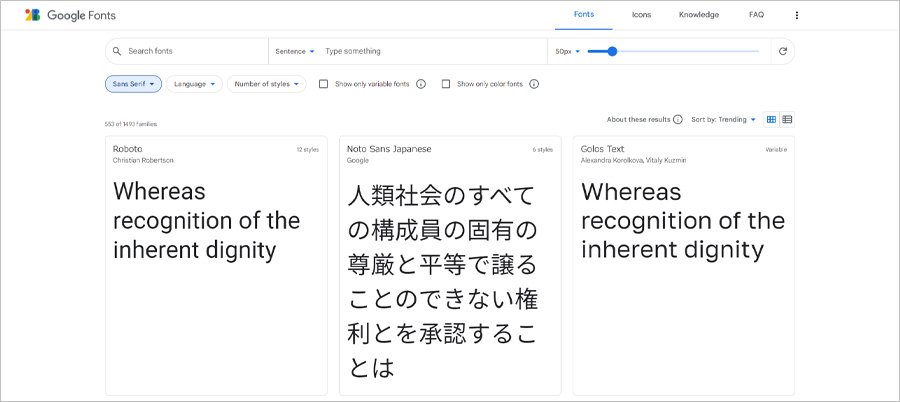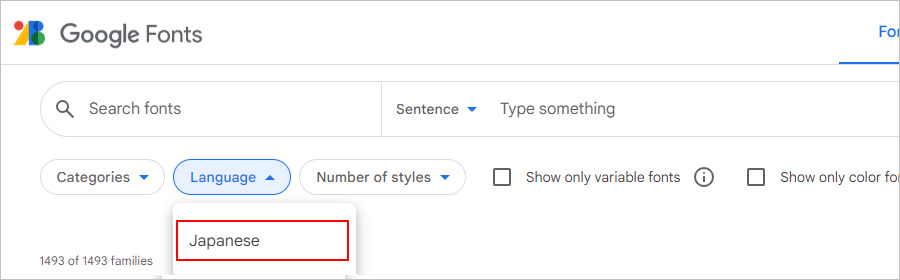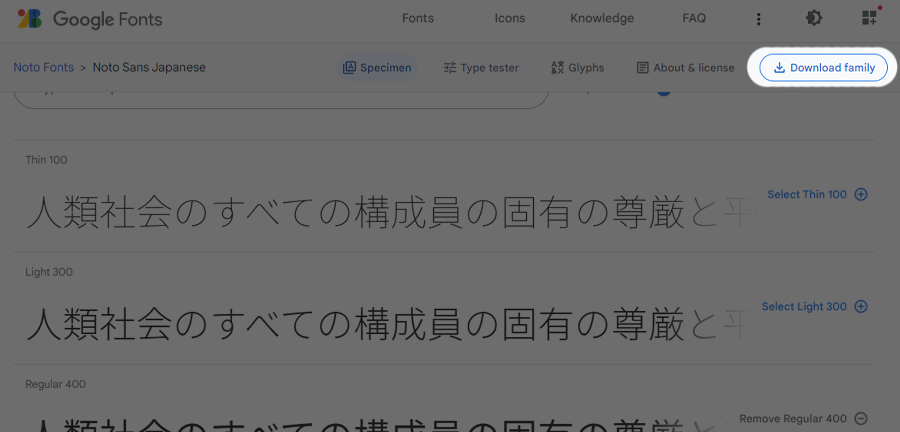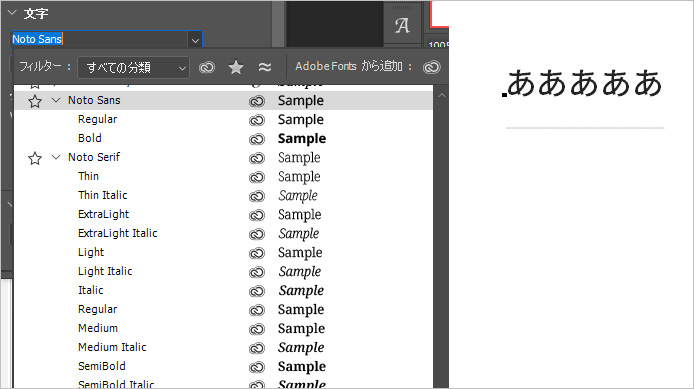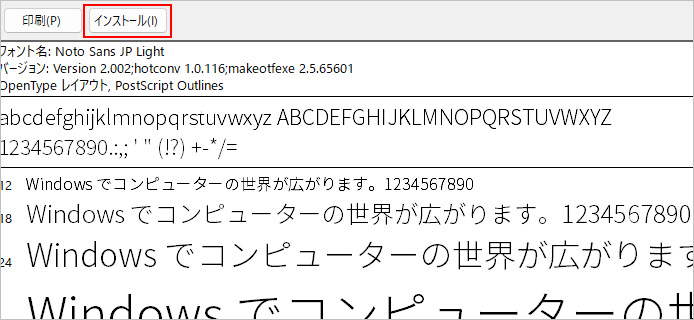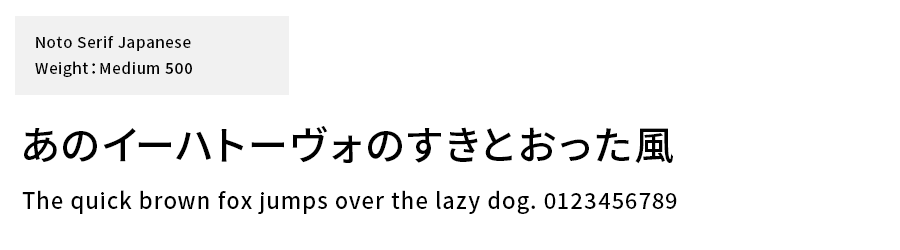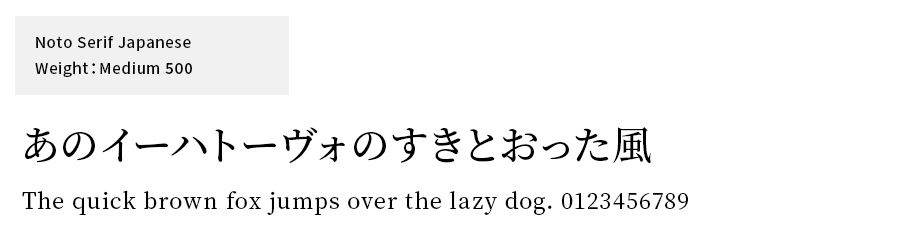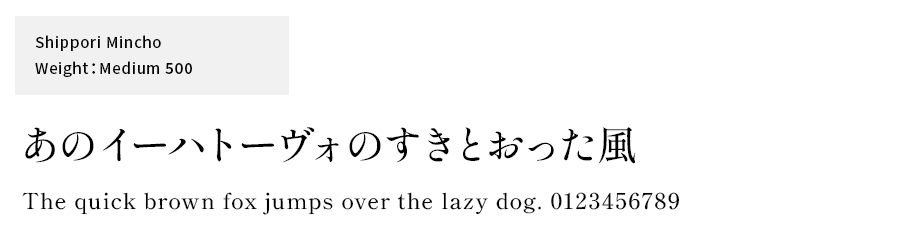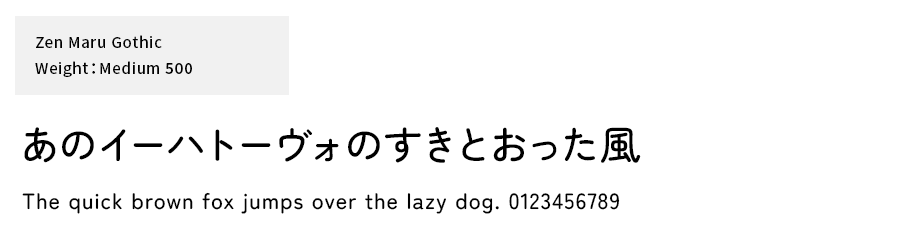
【無料で綺麗】Google Fontsのダウンロード・インストール方法、使い方を解説します!
Google Fontsとは
Google Fontsとは、その名の通りGoogleが提供しているwebフォントです。
どれも無料で利用することができ、様々な言語に対応しています。
windowsなどのOS標準インストールのフォントにはない、綺麗で魅力的なフォントがたくさんあるため、webサイト等のデザインで多用されています。
私がGoogle Fontsでよく使うフォントピックアップ
Noto Sans Japanese(日本語対応)
「Noto」シリーズは、GoogleがAdobeと共同開発したゴシック体のフォントファミリーです。中でもNoto Sans JPは日本語のみのフォントに特化しています。
太さ(Weight)のバリエーションも多く、「Thin 100」から「Black 900」まで6種類あります。
スマートフォンなどでも読みやすいよう設計されており、収録漢字も豊富かつ高品質なため、利用の幅はとても広いです。
「Noto Sans」はデジタル庁でも使用されていることが話題になりました。
Noto Serif Japanese(日本語対応)
Noto Sansのセリフ体(明朝体)バージョンの「Noto Serif Japanese」。こちらもNoto Sansと同様の使いやすさです。
太さ(Weight)はNoto Sansより1つ多く、7種類あります。
Shippori Mincho(日本語対応)
東京築地活版製造所の五号系活字をベースにした、筆運びの美しさが感じられる、オールドスタイル明朝体フリーフォントです。
太さ(Weight)は5種類と豊富です。
Zen Maru Gothic(日本語対応)
明朝体や角ゴシック体とは異なり、漢字の角などがやわらかくなめらかです。安心感を演出する時などに使われることが多いです。
太さ(Weight)は5種類となっており、太さによって印象ががらりと変わるため、なにかと重宝するフォントです。
Roboto(欧文のみ)
Robotoは、GoogleがAndroidのシステムフォントとして開発したサンセリフ(ゴシック体)のフォントです。Androidやchrome OSでのデフォルトフォントとして利用されています。
太さ(Weight)や斜体(Italic)などスタイル違いで12種類あります。欧文のみで日本語は収録されていません。
今回はGoogle Fontsのダウンロード方法と使い方、また使いやすいフォントについてまとめました。
フォントはデザインの印象を決めるとても大事な要素です。
「Google Fonts」にはこの他にも魅力的なフォントがたくさんありますので、どんどん活用してデザインの幅を広げていきましょう。